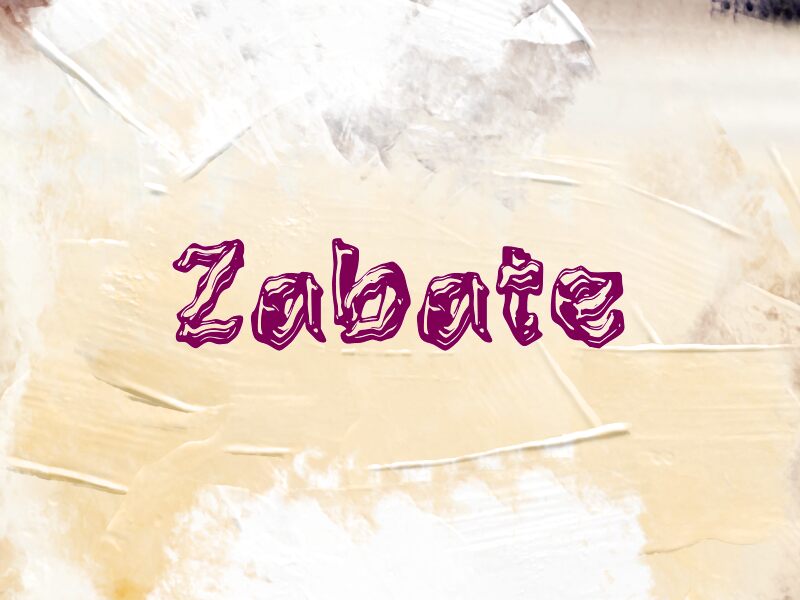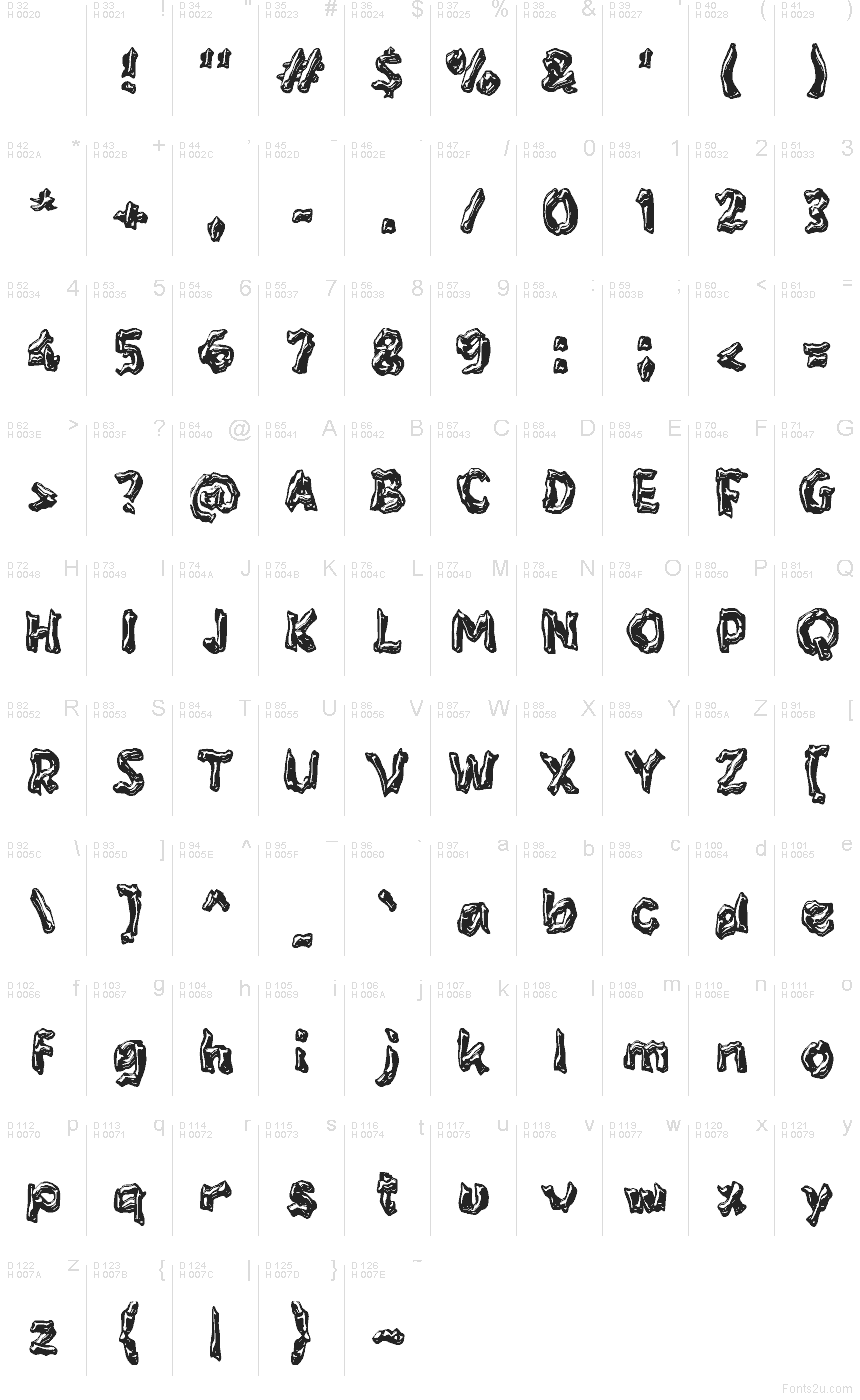
Zabate, créée par Wep, est une police d'affichage gratuite au style fondu, avec une attitude souple et artisanale. Les lettres semblent douces et déformées, comme si elles étaient tirées d'un liquide épais ou de plastique fondu, avec des bords ondulés et des formes généreuses qui gardent un style ludique plutôt que brut.
Zabate trouve naturellement sa place sur les affiches, les visuels musicaux, les flyers de clubs, les graphismes streetwear et les packagings où vous souhaitez une typographie à la fois décontractée et originale. En tant que police gratuite, elle est parfaite pour les titres courts, les génériques et les logos, car ces formes gonflées et ondulantes font tout le travail visuel par elles-mêmes.
Zabate